Bagi seorang desainer, memakai font Arabic untuk membuat desain di event tertentu sangat diperlukan.
Misalnya untuk membuat desain mengenai Maulid Nabi, Idul Fitri, Idul Adha dan lainnya.
Tujuannya supaya desain yang kamu buat dengan teks dari font Arabic tersebut menjadi selaras. Hal inilah yang bisa menambahkan nilai lebih ke desain kamu.
Kalau kamu ingin membuat desain islami, berikut Uplotify.id akan memberikan rekomendasi daftar font Arab keren yang bisa didownload gratis.
Daftar Font Arab Terbaik untuk Desain Islami
Daftar font Arab yang disediakan terdiri dari murni teks Hijaiyah dan ada juga teks abjad namun desain menyerupai tulisan Arab.
- 30. Kahlil Font
- 31. Ramadhan Karim
1. B Arshia Font
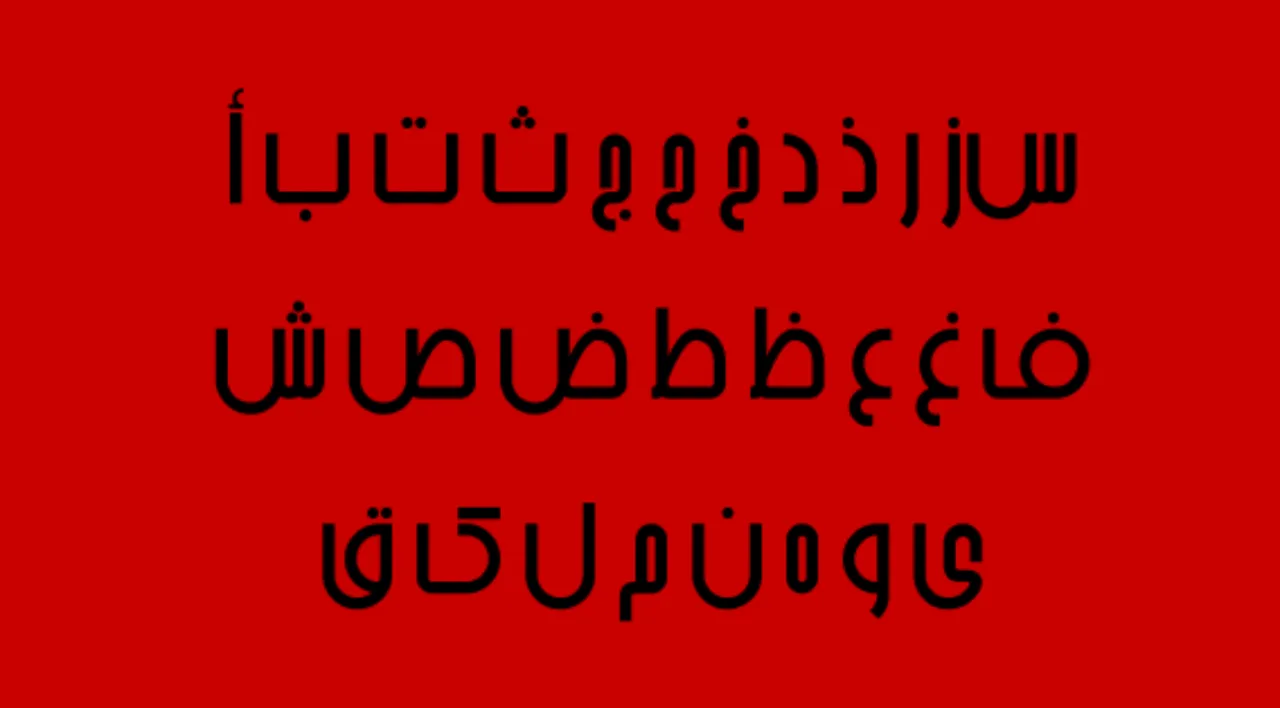
Untuk kamu yang mencari font Arab dengan teks Hijaiyah, maka kamu bisa mendownload B Arshia Font.
Font ini memiliki desain sedikit kaku, sehingga terlihat seperti huruf Hijaiyah modern.
Desain huruf Hijaiyah di B Arshia Font juga cukup banyak dan terbagi menjadi 3 jenis.
Selain huruf Hijaiyah, di font ini kamu juga akan mendapatkan beragam simbol gaya tulisan Arab.
2. B Davat Font
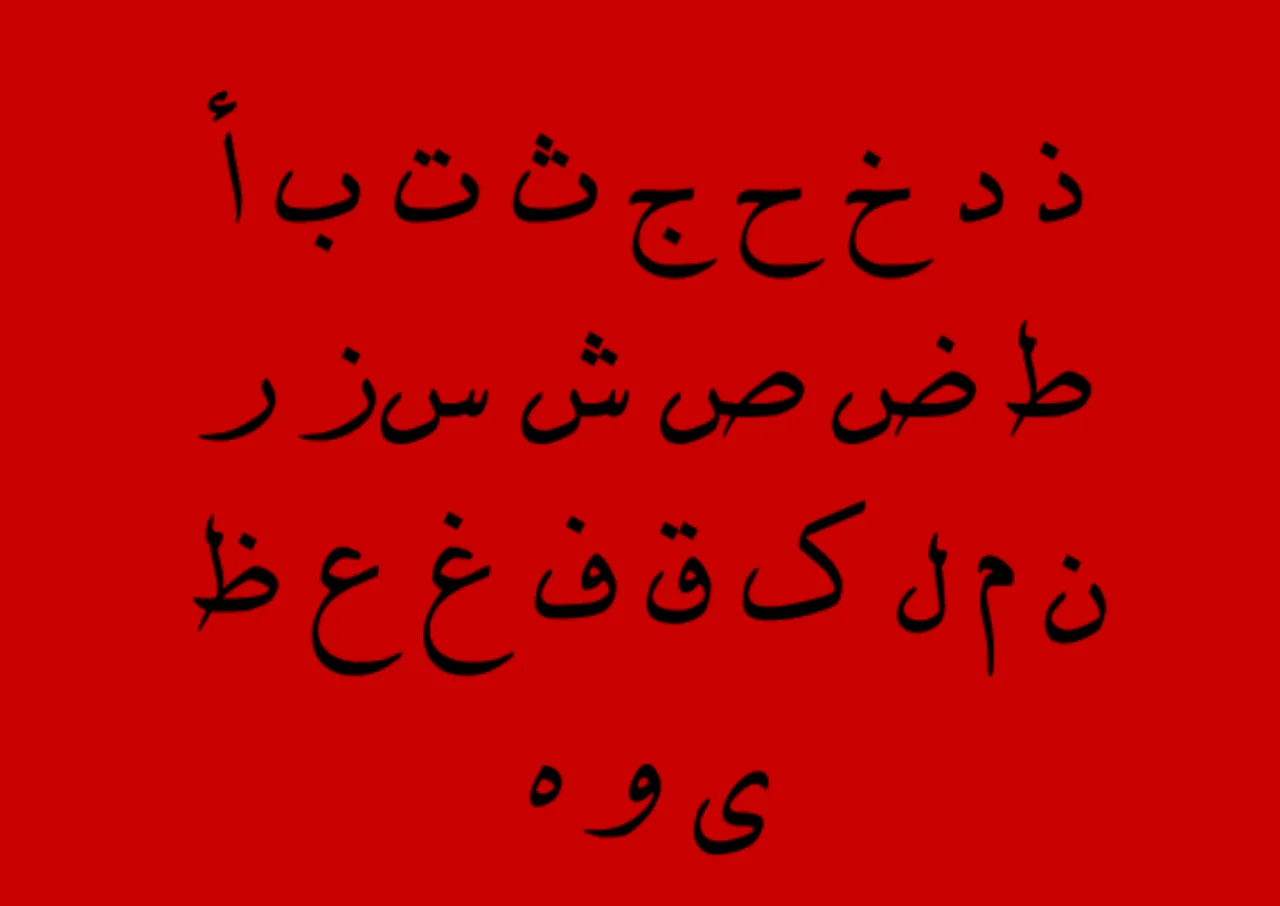
Selanjutnya ada B Davat font. Font ini juga sama, terdiri dari huruf Hijaiyah namun dengan desain sederhana.
Jumlah karakter yang tersedia di B Davat ini cukup banyak, yaitu 250+. Umumnya terdiri dari 200+ huruf Hijaiyah dan sisanya terdiri dari beberapa simbol.
3. B Arabic Style Font
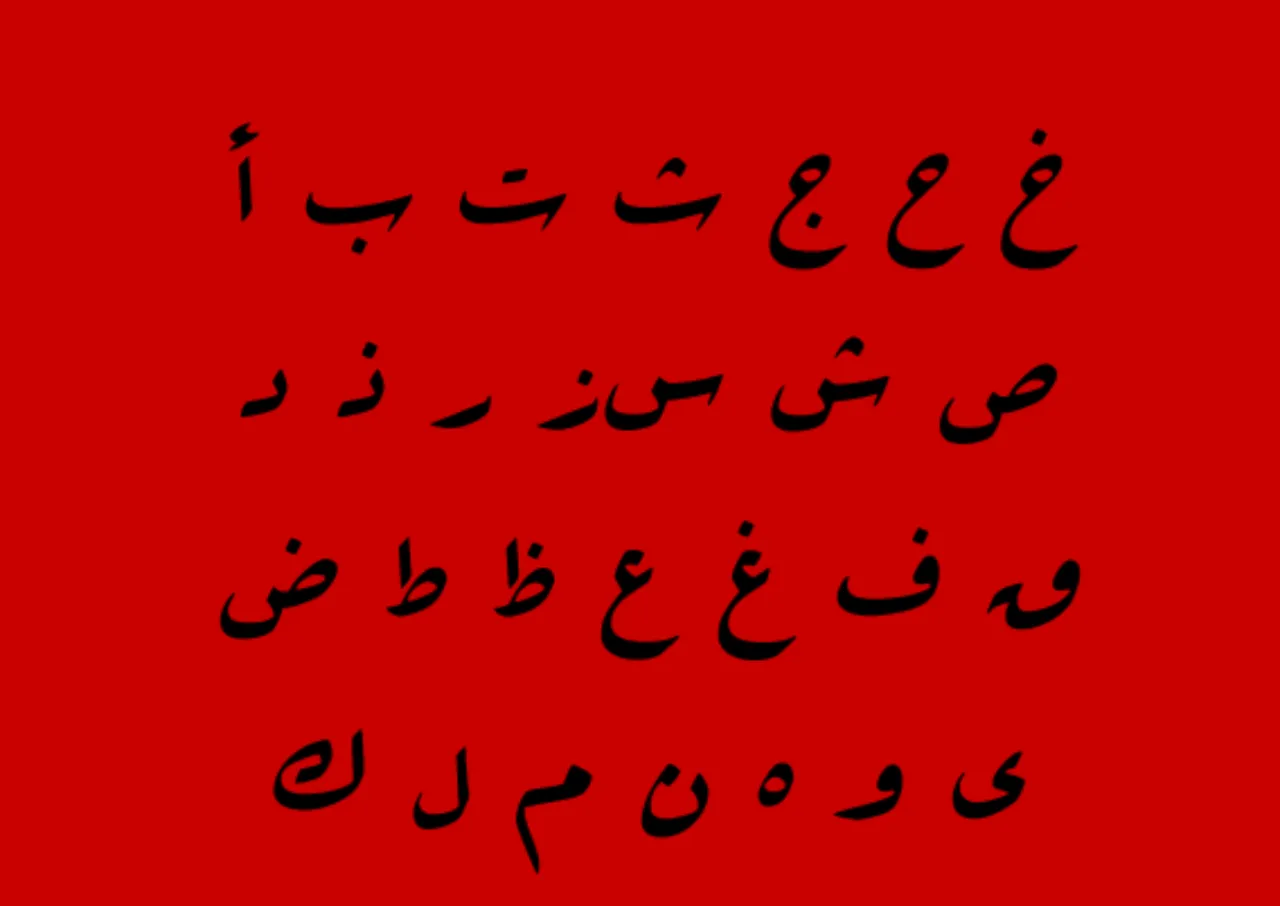
B Arabic Style font, merupakan sebuah font yang berisi huruf Hijaiyah modern dengan sedikit coretan.
Di font ini tidak hanya tersedia huruf Hijaiyah saja, melainkan lengkap dengan harakat dan huruf Arab-nya.
4. B Fantezy Font
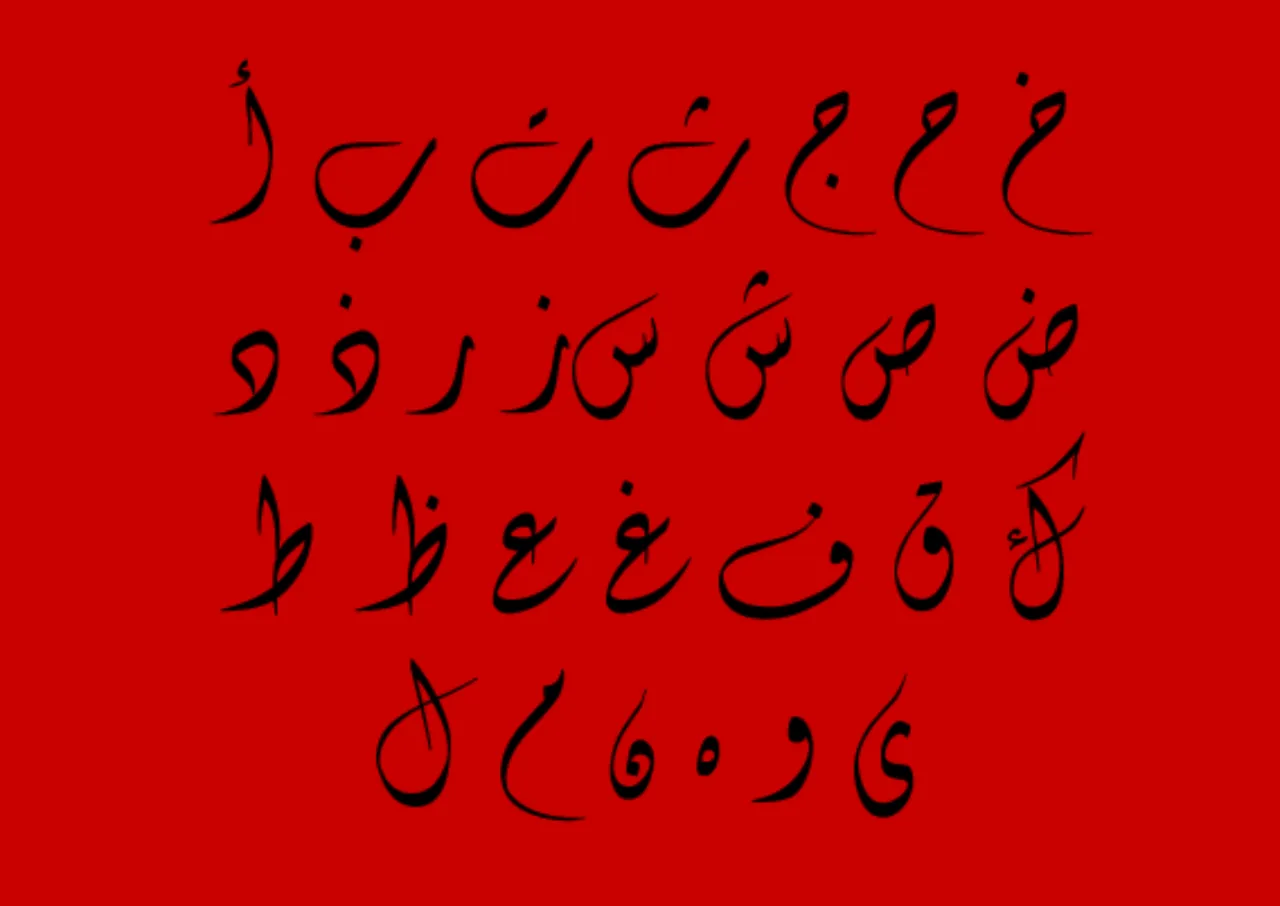
Kalau kamu ingin memakai desain huruf Hijaiyah yang lebih bergaya, B Fantezy font ini bisa jadi salah satu pilihan.
Di font ini berisi huruf Hijaiyah yang di desain dengan coretan cukup panjang. Font ini juga dilengkapi dengan harakat dan nomor Arab.
5. B Elham Font
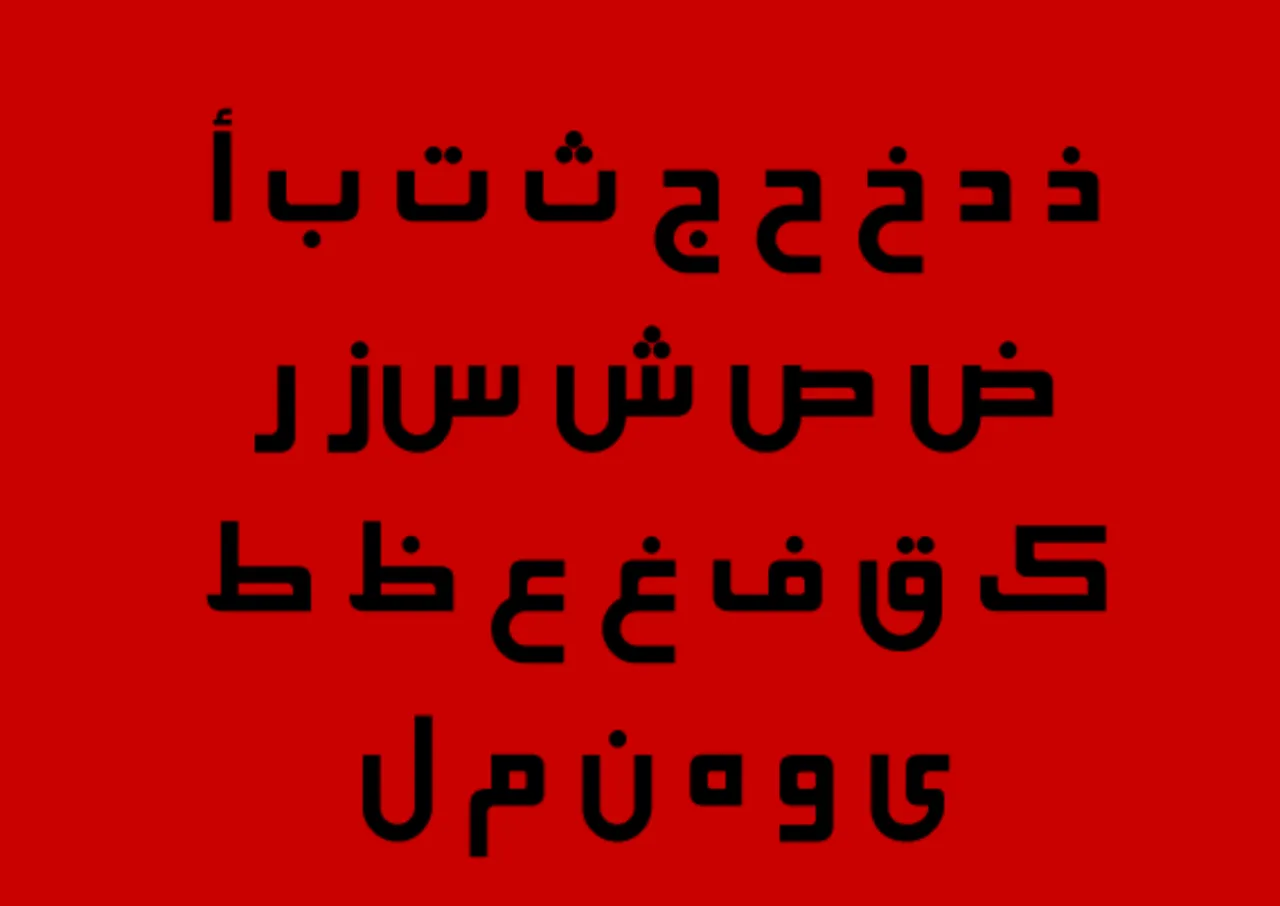
Lalu ada B Elham font yang memiliki desain menyerupai tulisan kaligrafi modern.
Bisa dibilang, font ini paling laris di download karena bentuknya yang bisa dipakai untuk beragam desain.
Jumlah karakter di B Elham font cukup banyak, yaitu sekitar 286. Terdiri dari huruf Hijaiyah, nomor Arab, harakat dan simbol khusus.
6. B Esfehan Bold Font
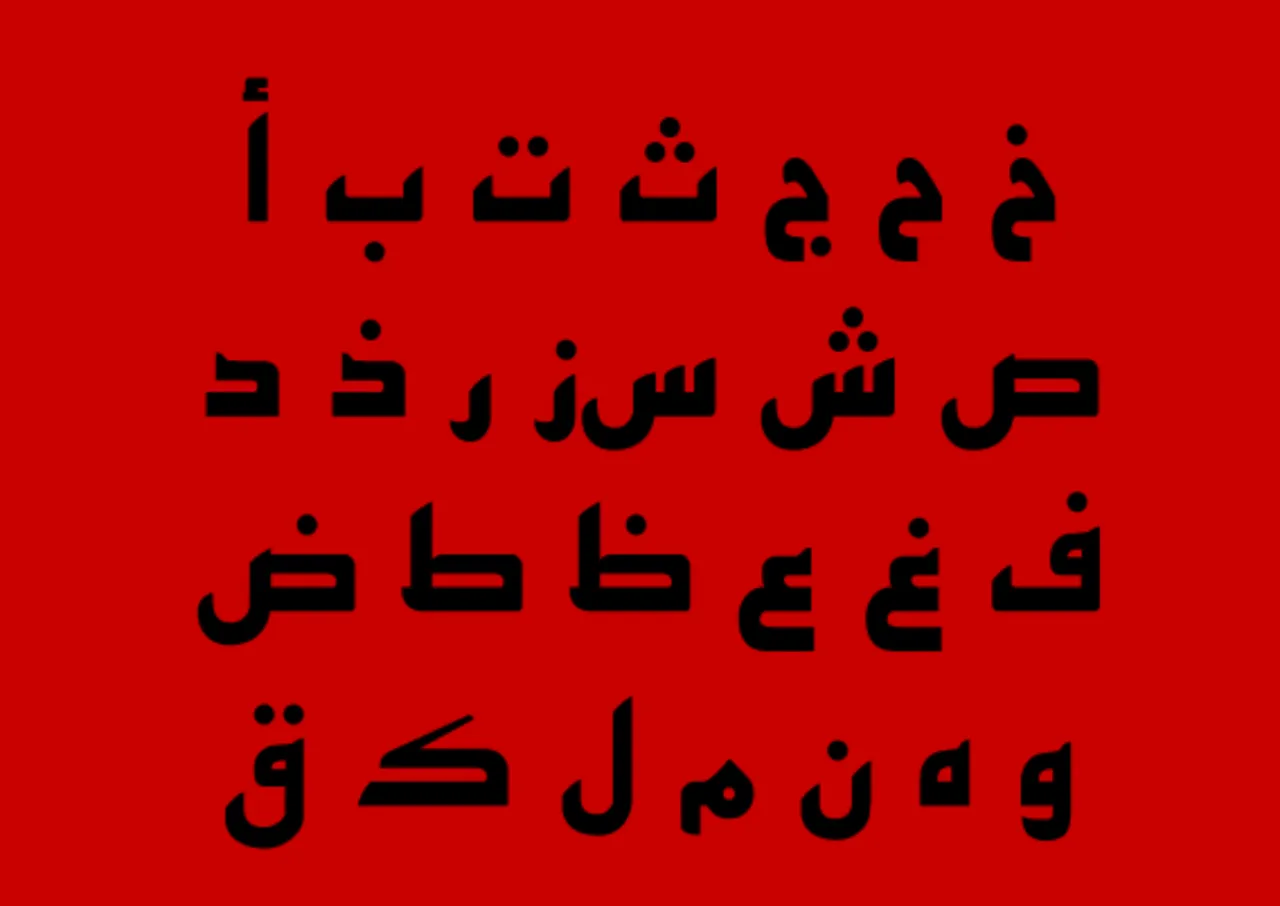
B Esfehan Bold font merupakan sebuah font yang memiliki desain mirip seperti B Elham, yaitu bertemakan kaligrafi modern.
Bedanya kalau B Elham desainnya tidak tebal, sedangkan B Esfehan Bold sangat tebal.
7. B Compset Font
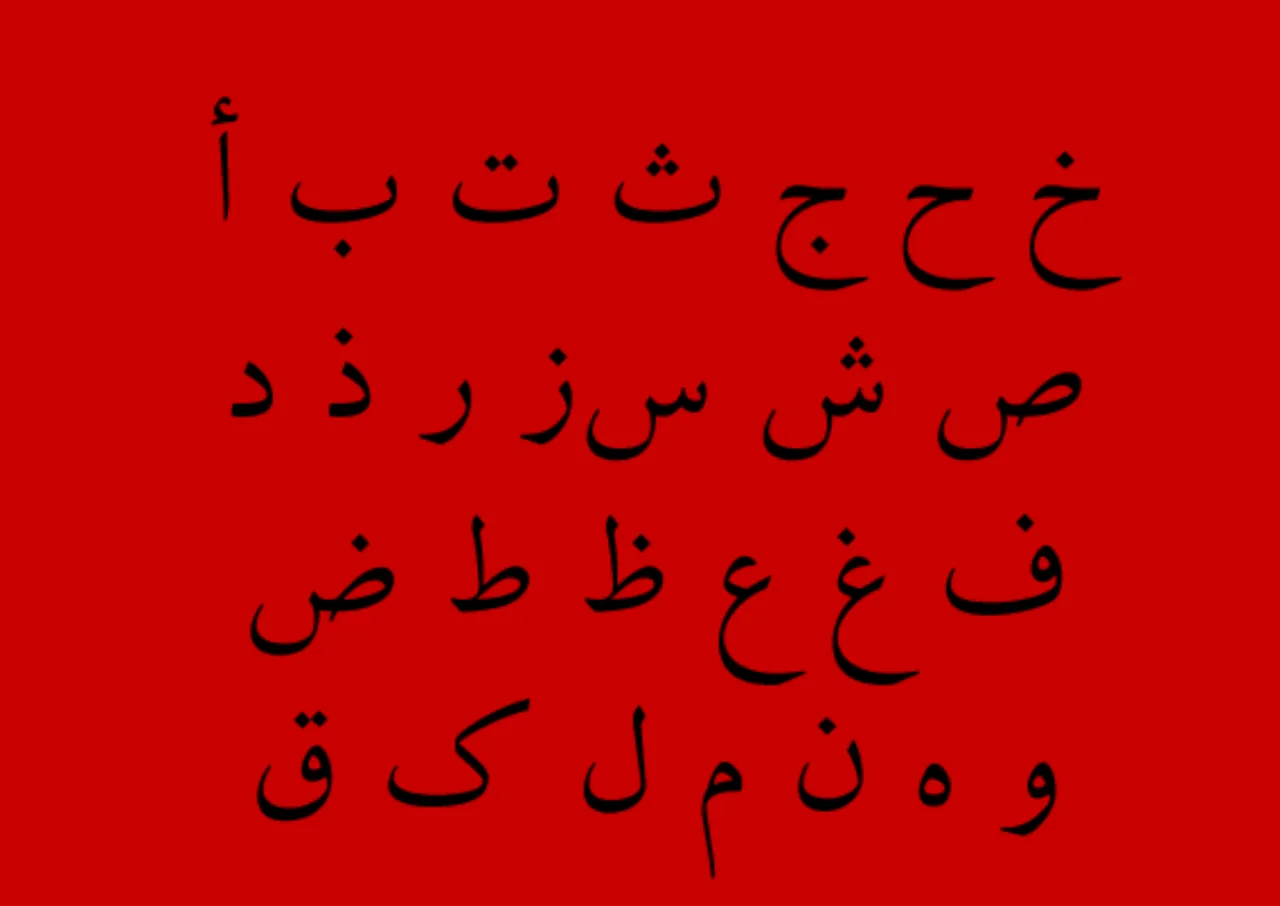
Lanjut ada B Compset font yang memiliki desain huruf Hijaiyah tipis. Font ini sangat cocok dipakai untuk kamu yang ingin membuat desain islami sederhana.
Di dalam B Compset font terdiri dari 286 karakter yang terdiri dari huruf Hijaiyah, simbol khusus, nomor Arab dan harakat.
8. B Koodak Outline Font
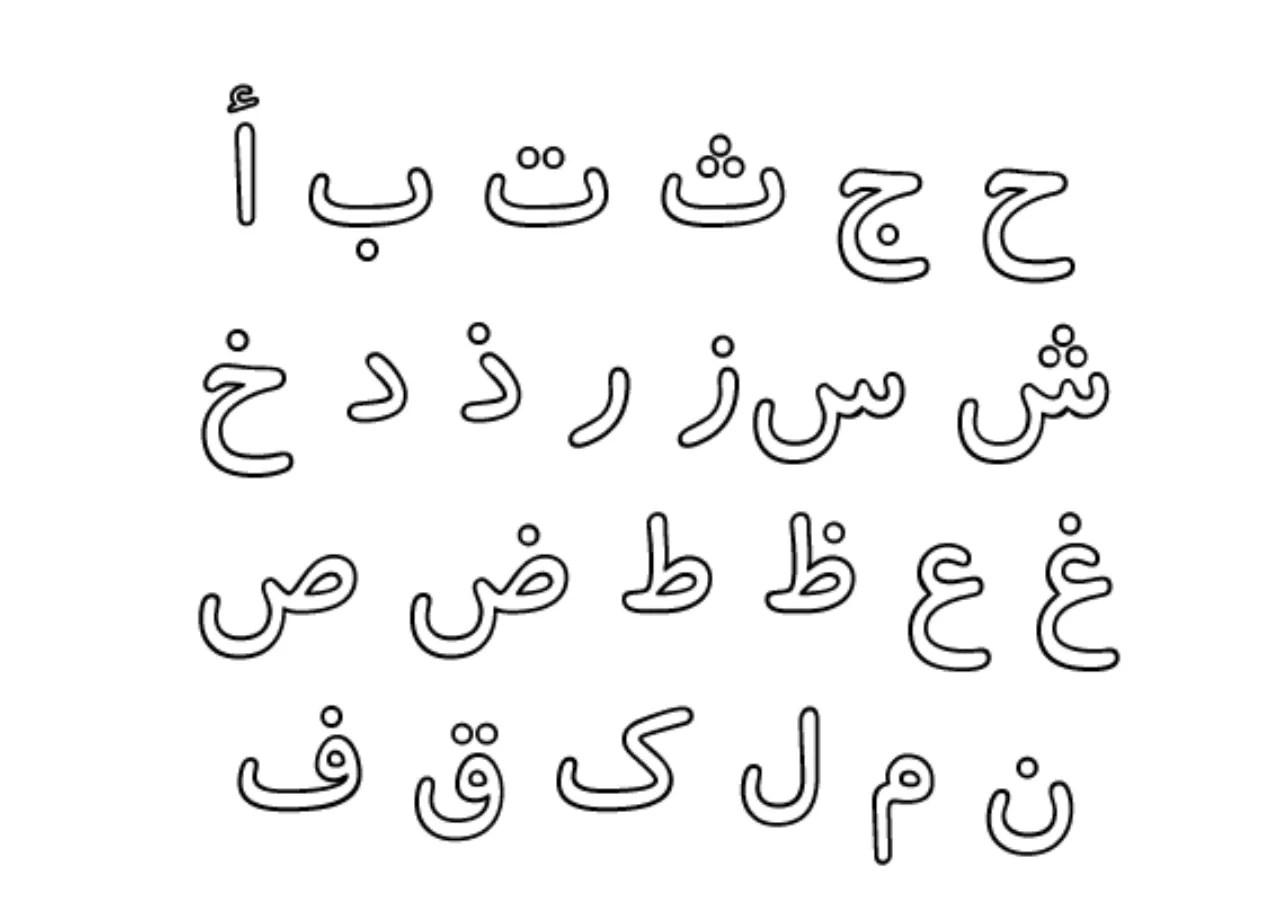
Kalau kamu ingin memakai desain huruf Hijaiyah tanpa fill, B Koodak Outline ini sangat direkomendasikan.
Sesuai dengan namanya, font ini hanya memiliki outline saja tidak ada fill. Sehingga bisa membuat desain kamu menjadi lebih unik.
9. Traditional Arabic Font
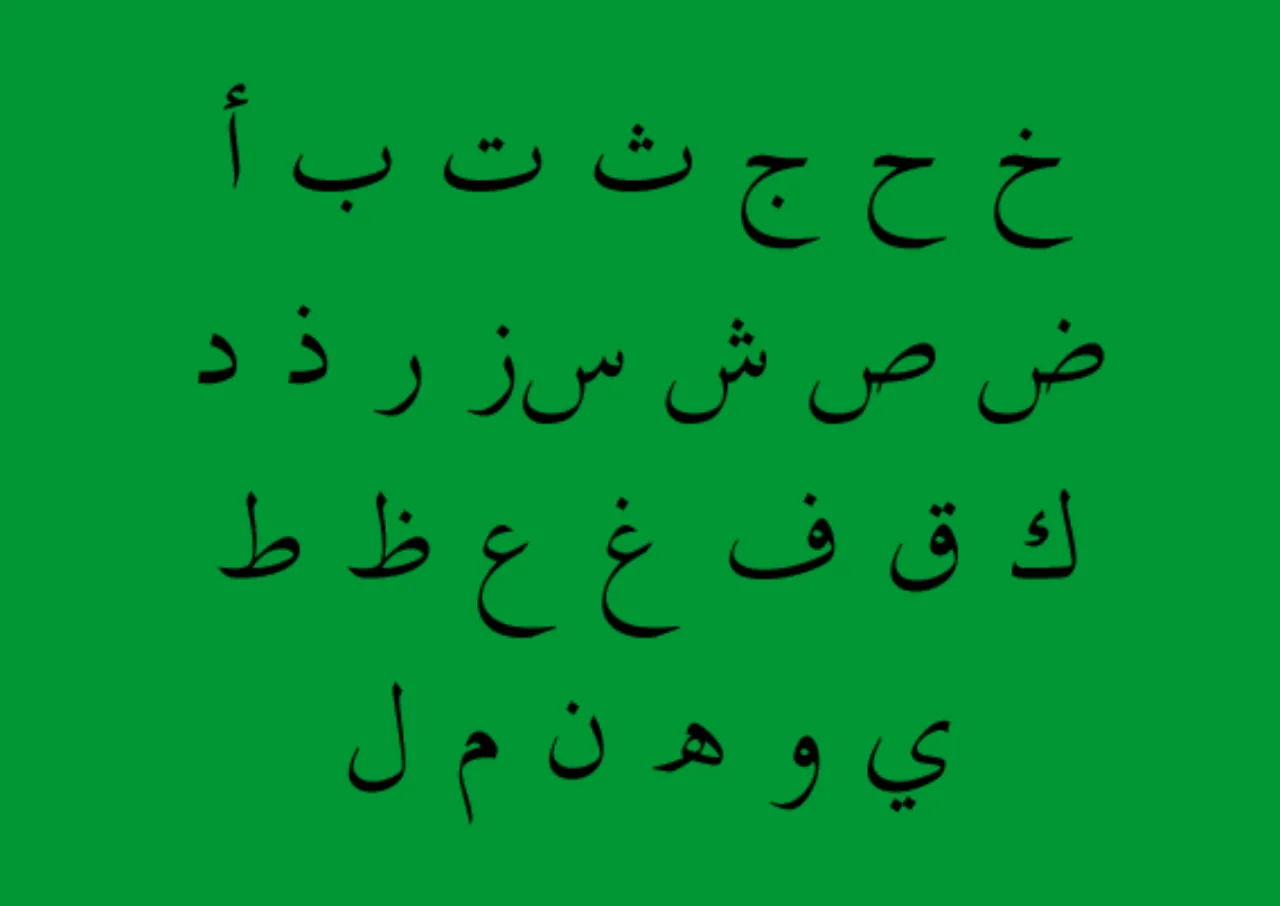
Traditional Arabic merupakan sebuah font yang memiliki desain huruf Hijaiyah model lama. Font ini sangat cocok dipakai untuk membuat desain sederhana.
Selain itu, font ini juga menyediakan banyak karakter. Mulai dari huruf Hijaiyah, harakat dan nomor Arab.
10. B Jadid Bold Font
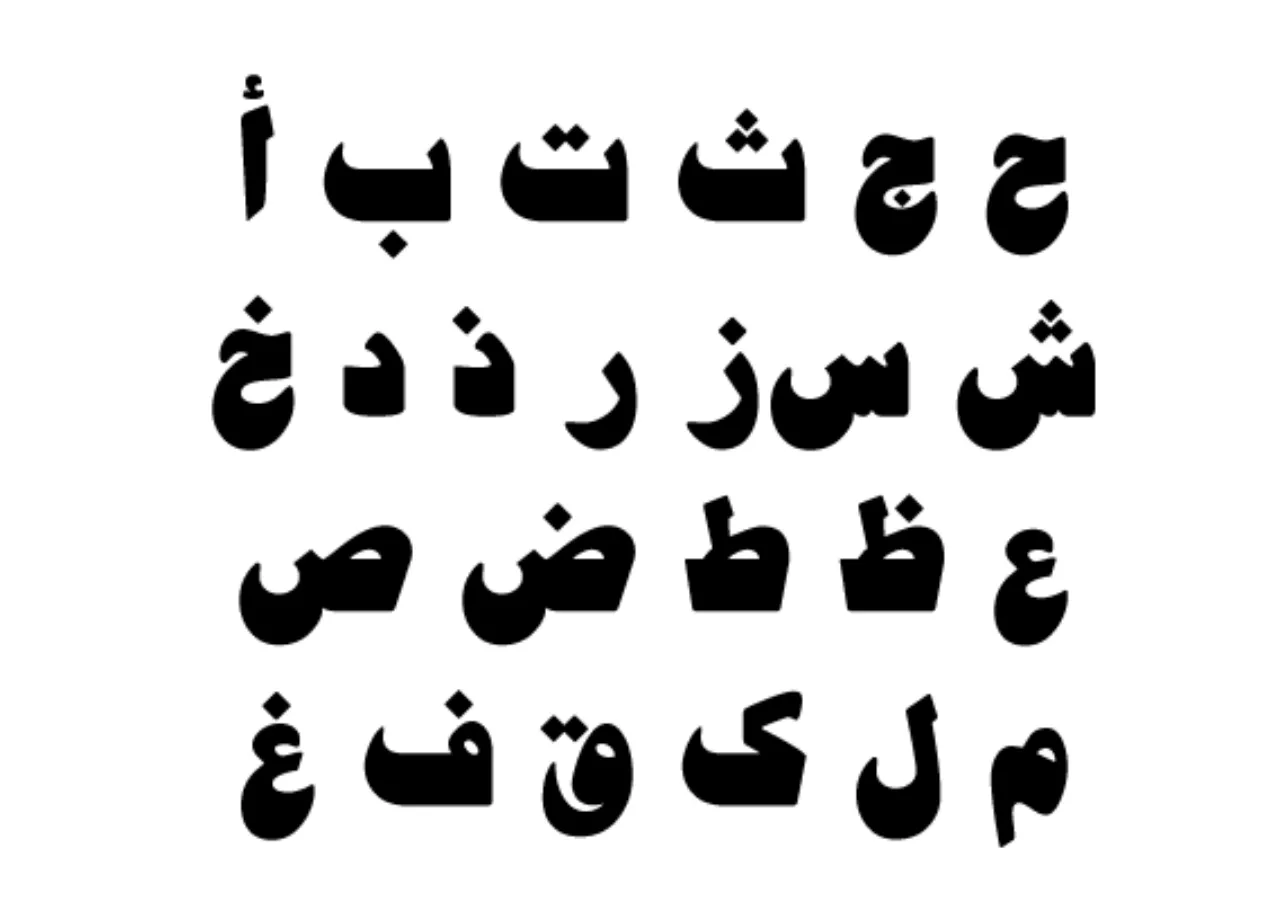
B Jadid Bold adalah font yang memiliki huruf Hijayah dengan desain brush painted. Karena memakai desain brush, membuat font ini terlihat tebal.
Font ini sangat cocok dipakai untuk desain Islami modern. Karena bisa dipadukan oleh beragam desain saat ini.
11. Simplified Arabic Font
Untuk font arab versi simpel, Simplified Arabic font ini bisa menjadi salah satu pilihan kamu.
Desain di font ini sangat sederhana namun ada sedikit efek kaku sehingga terlihat menarik.
12. B Ferdosi Font
Selain Simplified Arabic, B Ferdosi font juga sangat direkomendasikan untuk dipilih kalau ingin mencari desain font arab sederhana.
Bedanya di font ini memiliki karakter yang lebih lengkap. Karena terdiri dari huruf Hijaiyah, harakat, nomor Arab dan simbol-simbol khusus.
13. Kacst Book Font
Jika kamu mencari font yang menyediakan huruf Hijaiyah juga abjad dengan desain Arab, Kacst Book ini cukup direkomendasikan.
Karena dengan memakai font ini, kamu tidak perlu lagi mengunduh jenis font berbeda. Semuanya sudah tersedia dalam 1 file font Kacst Book tersebut.
14. PakType Naqsh Font
PakType Naqsh font ini memiliki spesifikasi sama seperti Kacst book. Hanya saja desain huruf Hijaiyah dan abjad di font ini memakai desain modern.
Font yang terdiri dari 1721 karakter ini sangat direkomendasikan. Karena selain punya desain lengkap dan jumlah karakter lengkap juga bisa dipadukan oleh berbagai macam desain acara islami saat ini.
15. Afarat Ibn Blady Font
Selanjutnya untuk desain huruf abjad dengan desain Hijaiyah, Afarat Ibn Blady font bisa jadi pilihan.
Font ini terbilang cukup lengkap. Karena terdiri dari huruf abjad, nomor, simbol dan beberapa harakat.
16. Alhambra Font
Alhambra font yang memiliki spesifikasi serupa dengan sebelumnya.
Namun di Alhambra font ini memiliki desain kaligrafi dan teksnya lebih terbaca di bandingkan Afarat yang mengusung huruf Hijaiyah.
Font ini sangat cocok dipadukan dengan font B Elham. Karena sama memiliki desain kaligrafi.
Baca Juga:
17. Catharis Bedouin Font
Catharis Bedouin, font ini memiliki desain seperti huruf bersambung. Namun dipadukan dengan desain Arabic sehingga menampilkan karakter unik.
Selain karakter huruf yang unik, di font ini juga memiliki simbol khusus dengan desain Arab.
18. Arabic Lamp Font
Kalau bicara soal font arab unik, Arabic Lamp bisa menjadi salah satu pilihan.
Alasannya karena font ini memiliki desain menyerupai lampu lampion yang biasa ada di arab.
Font Arabian Lamp ini terdiri dari huruf dan nomor dengan desain serupa.
19. Kara Ben Nemsi Font
Kara Ben Nemsi adalah sebuah font yang memiliki karakter dengan desain brush tipis.
Selain mengusung desain brush, font ini juga dipadukan dengan sedikit desain Arabic.
Kelengkapan dari font ini juga cukup baik. Karena sudah terdiri dari huruf besar, kecil, angka, simbol dan beberapa karakter khusus.
20. Arab Dances Font
Hampir mirip seperti desain di atas karena sama memakai desain brush tipis yang dipadukan dengan tulisan Arabic.
Namun bedanya Arab Dances ini memiliki desain yang lebih kaku dan jelas terbaca. Menariknya, font ini memiliki simbol khusus desain islami, seperti karakter icon sslam.
21. Running Smobble Font
Running Smobble ini memiliki desain coretan yang dipadukan dengan tulisan Arabic. Namun bisa dikatakan juga memiliki desain sedikit abstrak.
Meskipun begitu, font ini sangat cocok dipakai untuk membuat desain islami yang kreatif. Utamanya untuk perlombaan islami.
22. XXI Arabian Onenightstand Font
Selanjutnya ada XXI Arabia Onenightstand font. Font ini sebenarnya lebih kental ke huruf abjad dengan desain coretan. Namun dipadukan sedikit desain tulisan Arab.
Oleh karena itu, membuat font ini terlihat sangat menarik.
Karena desainnya yang sangat modern, membuat font ini sangat laris. Bahkan sudah didownload oleh 1.5 juta orang.
Baca Juga:
23. Pseudo Saudi Font
Kalau Pseudo Saudi font ini kebalikannya, karena lebih kental ke tulisan Arabic. Di font ini, kamu akan mendapatkan huruf abjad yang memakai huruf Hijaiyah.
Menariknya, font ini bisa dikatakan cukup lengkap. Karena terdiri dari huruf besar, kecil, angka dan beberapa simbol khusus.
24. Mohammed Font
Mohammed font menyediakan beragam karakter huruf abjad dengan desain unik. Selain unik, font tersebut juga dikombinasikan dengan tulisan Arab supaya lebih menarik.
Font ini, bisa kamu pakai untuk banyak keperluan desain bernuansa islami. Seperti acara Maulid, Idul Adha dan sebagainya.
25. Syawal Khidmat Font
Font yang dibuat oleh Gunarta, desainer asal Indonesia ini memiliki desain arab yang cukup kental.
Meskipun demikian, huruf abjad dari font Syawal Khidmat ini masih jelas terbaca. Mengenai kelengkapan, font ini memiliki 74 karakter yang terdiri dari simbol khusus, angka dan huruf.
26. Siti Maesaroh Font
Font karya Gunarta selanjutnya adalah Siti Maesaroh. Font Siti Maesaroh memiliki desain tipis dan seperti huruf sambung.
Namun dikombinasikan dengan sedikit tulisan Arabic. Seperti penambahan titik, pemakaian huruf Hijaiyah di beberapa karakter dan lainnya.
27. Mukadimah Font
Berikutnya ada Mukadimah Font. Font dengan desain kaligrafi modern ini sangat cocok dipadukan untuk beberapa desain islami.
Misalnya seperti acara Idul Fitri, Idul Adha, Lomba Islami dan sebagainya. Jumlah karakternya juga cukup lengkap, karena terdiri dari huruf abjad besar, kecil dan anga.
28. Ramadhan Amazing Font
Ramadhan Amazing merupakan salah satu font bertemakan Arab terkenal yang sudah didownload lebih dari 100 ribu kali.
Font bertemakan islami ini sangat cocok untuk berbagai macam desain. Juga cocok dipadukan dengan berbagai macam warna.
29. Sketsa Ramadhan
Sketsa Ramadhan merupakan font yang didesain oleh HPTypework, salah satu studio Indonesia yang aktif membuat font.
Sketsa Ramadhan sendiri mengusung font islami yang bertemakan bulan puasa. Selain itu, font ini juga cocok untuk desain idul fitri atau idul adha.
30. Kahlil Font
Kahlil Font merupakan font islami sederhana namun cukup direkomendasikan.
Pasalnya font ini sangat mudah dibaca, serta kental dengan nuansa Arab. Kamu bisa menggunakan font ini untuk berbagai macam tema desain.
31. Ramadhan Karim
Ramadhan Karim merupakan salah satu varian font berikutnya yang cocok untuk desain islami, terutama pada desain dengan tema bulan puasa.
Kamu bisa menggunakan berbagai macam jenis warna dengan font ini. Pasalnya font ini tetap bisa terlihat jelas dengan warna apapun.
Itulah rekomendasi daftar font Arab keren yang bisa kamu download secara gratis. Di pembahasan ini, tersedia dua jenis font Arab, yaitu huruf Hijaiyah dan abjad.
Oleh sebab itu, silahkan baca deskripsi yang diberikan lebih dulu sebelum mengunduhnya.